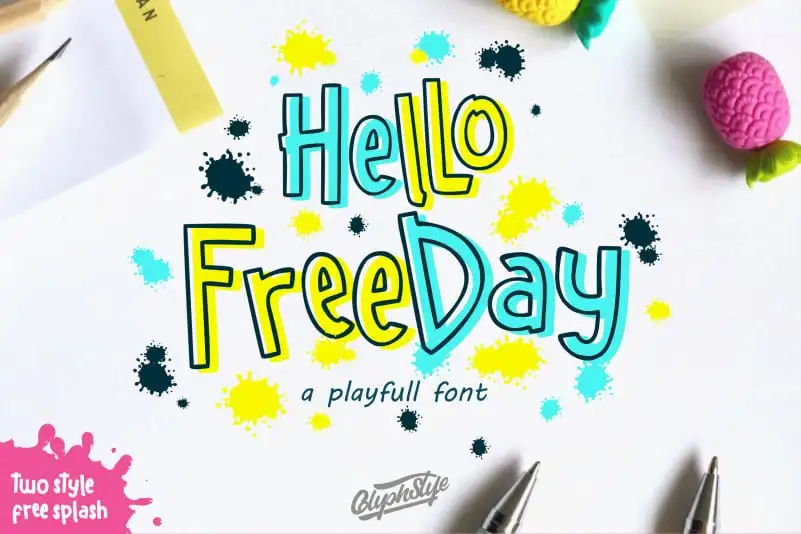
A ‘Hello Freeday 2 Style’ é uma fonte Display cheia de energia e humor que vem com duas versões distintas. Esta combinação originalmente chamada de ‘HelloFreeday’ tem um traço estilizado (outline) e um traço sólido (solid). As duas opções são ideais para projetos divertidos ou temáticas infantis, e encaixam-se perfeitamente em t-shirts, logotipos, anúncios, design de celebridades, cartões de visita, revistas de capa, selos, fotografias, marca d’água, convites, assinaturas e qualquer outro projeto que exija escritas animadas. A ‘Hello Freeday 2 Style’ é uma fonte ideal para quem busca colorir suas criações com uma pitada de alegria e originalidade em duas versões diferentes.